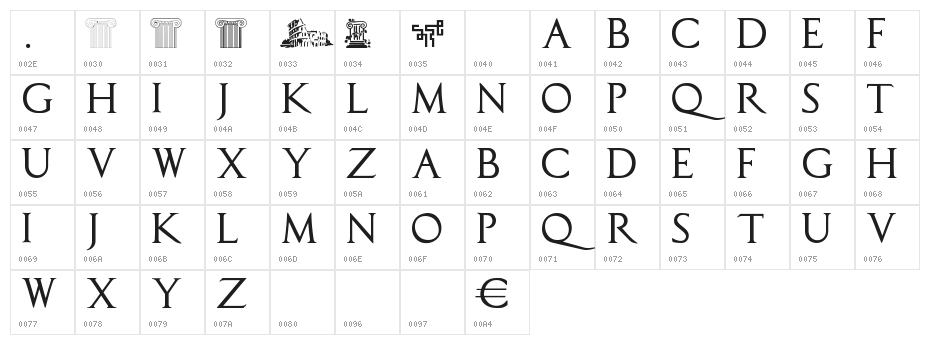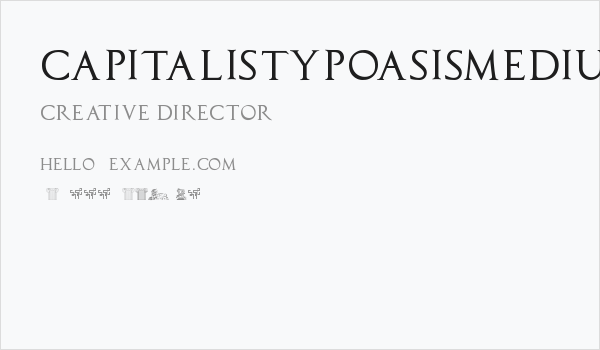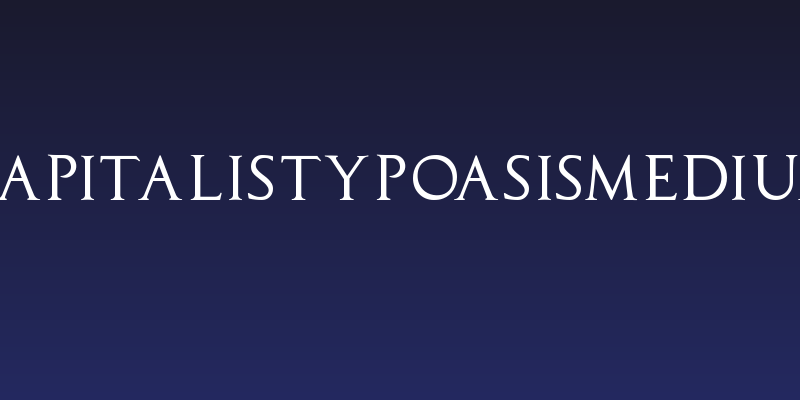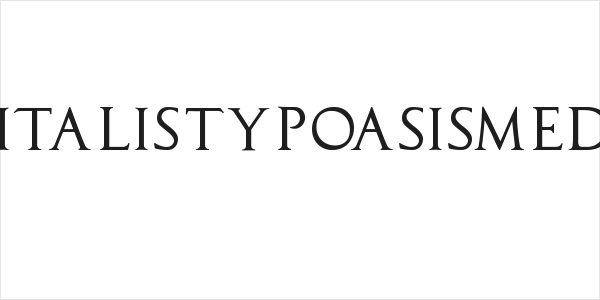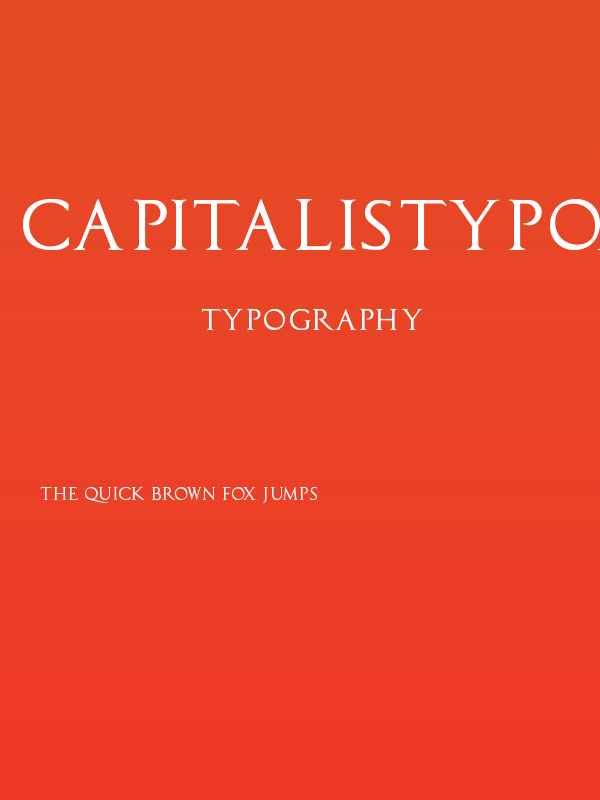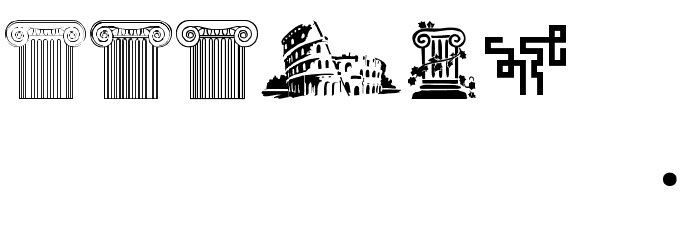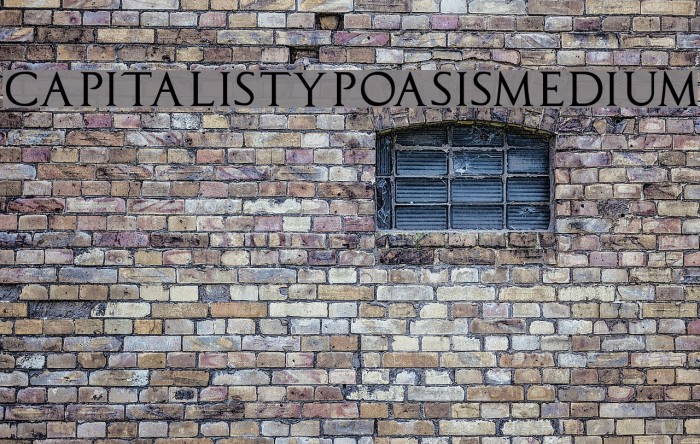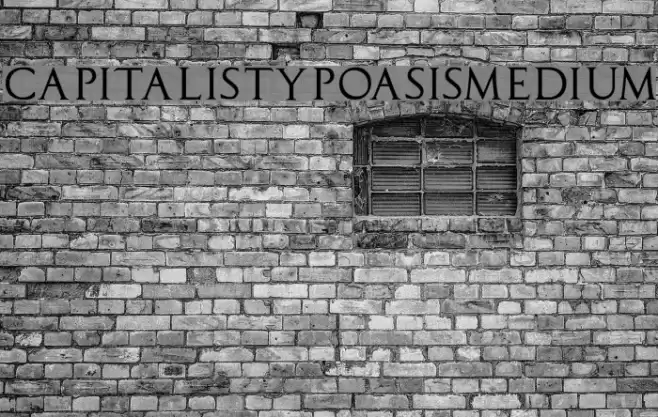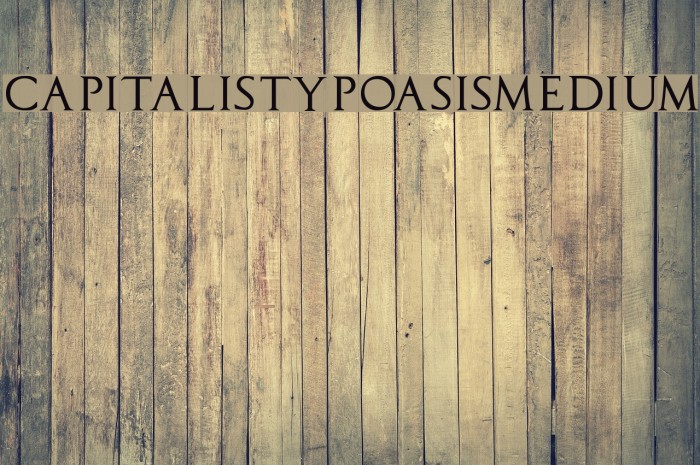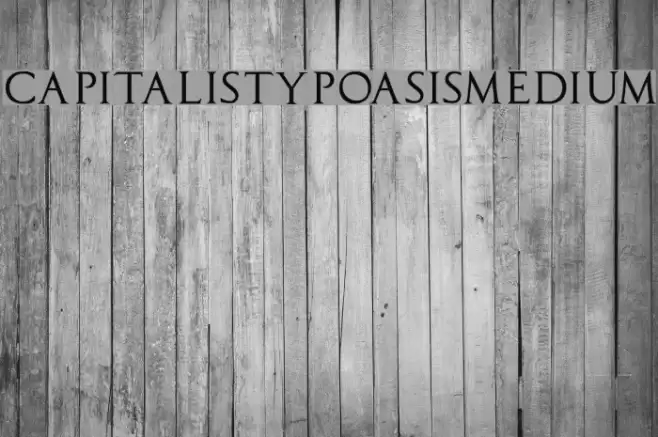
CapitalisTypOasisMedium Font
| Общий стиль | Classic |
| Область применения | Headlines, Logos, Formal documents |
| Рекомендуемые проекты | Ideal for use in formal invitations, historical publications, or branding that requires a touch of classical elegance. |